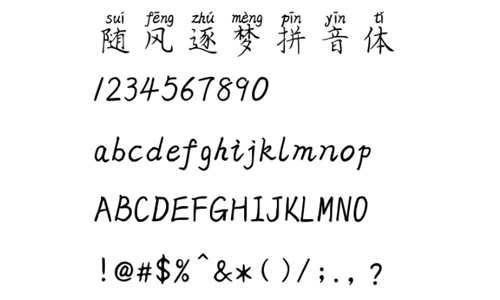
隨風逐夢拼音體字體是思雨字庫中一款非常漂亮的手寫拼音字體,“每一次與成功的交接,必定是艱苦奮斗的汗水與不甘失敗的淚水共同鑄就的。我愿做那勇敢的逐夢者,堅定地追尋夢的腳步。”——隨風逐夢體。本字庫是在國家標準簡體字庫GB2312所包含6763漢字的基礎上,又增加了近200常用字,已經覆蓋了大陸99.75%的漢字使用頻率,足以滿足日常需求。歡迎有需要隨風逐夢拼音體的朋友前來下載使用。